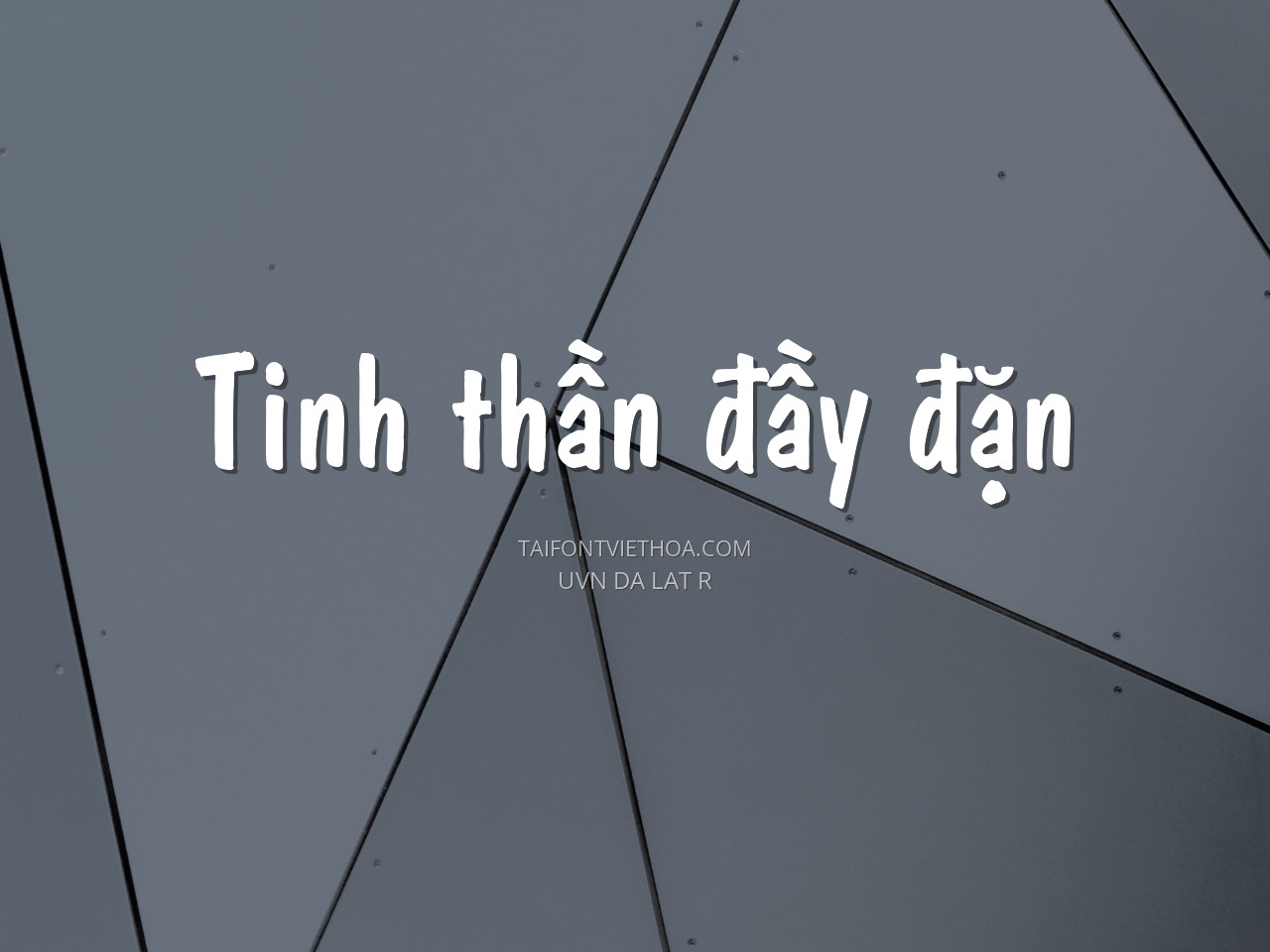
Giới thiệu về font UVN Da Lat
UVN Da Lat là một font chữ mang phong cách viết tay bay bổng, lấy cảm hứng từ vẻ thơ mộng và lãng mạn của thành phố sương mù. Với đường nét mềm mại, ngẫu hứng và giàu cảm xúc, font UVN Da Lat gợi lên hình ảnh những tấm bưu thiếp, nhật ký du lịch và ký ức thanh xuân dịu dàng. Font đã được sưu tầm và chia sẻ bởi thành viên Font Chuẩn, đồng thời được taifontviethoa.com tuyển chọn kỹ lưỡng và ứng dụng thực tế trong các thiết kế mang tính cảm xúc, văn hóa và nghệ thuật sáng tạo.
Đặc điểm thiết kế và ứng dụng của UVN Da Lat
Font UVN Da Lat thuộc nhóm viết tay (handwritten), với các nét bút uyển chuyển, đôi lúc ngắt quãng tự nhiên như một dòng cảm xúc chân thật. Các ký tự nghiêng nhẹ, tạo sự mềm mại và lãng mạn trong tổng thể thị giác. Font hỗ trợ đầy đủ tiếng Việt và thích hợp để trình bày các nội dung cảm xúc, nhẹ nhàng, riêng tư hoặc hoài niệm.
Ứng dụng lý tưởng cho các thiết kế như: bìa sách du ký, thiệp viết tay, poster văn hóa, bài thơ thị giác, trang blog cá nhân và ấn phẩm truyền cảm hứng. Ngành nghề phù hợp gồm: du lịch, sáng tạo nội dung, giáo dục, thiết kế mỹ thuật, truyền thông cảm xúc và sản phẩm handmade.